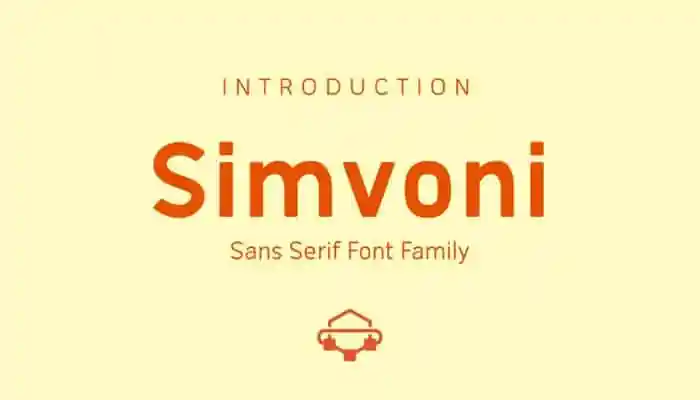
Simvoni Sans Serif Font – Download Grátis
A Simvoni Sans Serif Font é uma elegante tipografia moderna criada pelo designer AmruID, disponível na plataforma 99designs. Ela combina a simplicidade e limpeza do sans-serif com um toque de sofisticação que permite sua utilização em uma ampla gama de aplicativos gráficos, desde criação de logomarcas e identidades corporativas até embalagens de produtos e cartões de visita. A Simvoni é leve e equilibrada, tornando-a perfeitamente adequada para textos grandes como títulos ou nomes, oferecendo um alto nível de legibilidade e reconhecimento. Suas linhas arredondadas dão uma aparência elegante que a faz se destacar, sem perder o clima moderno que tanto os profissionais do design valorizam. Uma excelente escolha para quem busca uma fonte sofisticada e funcional, capaz de ressaltar em qualquer projeto visual.